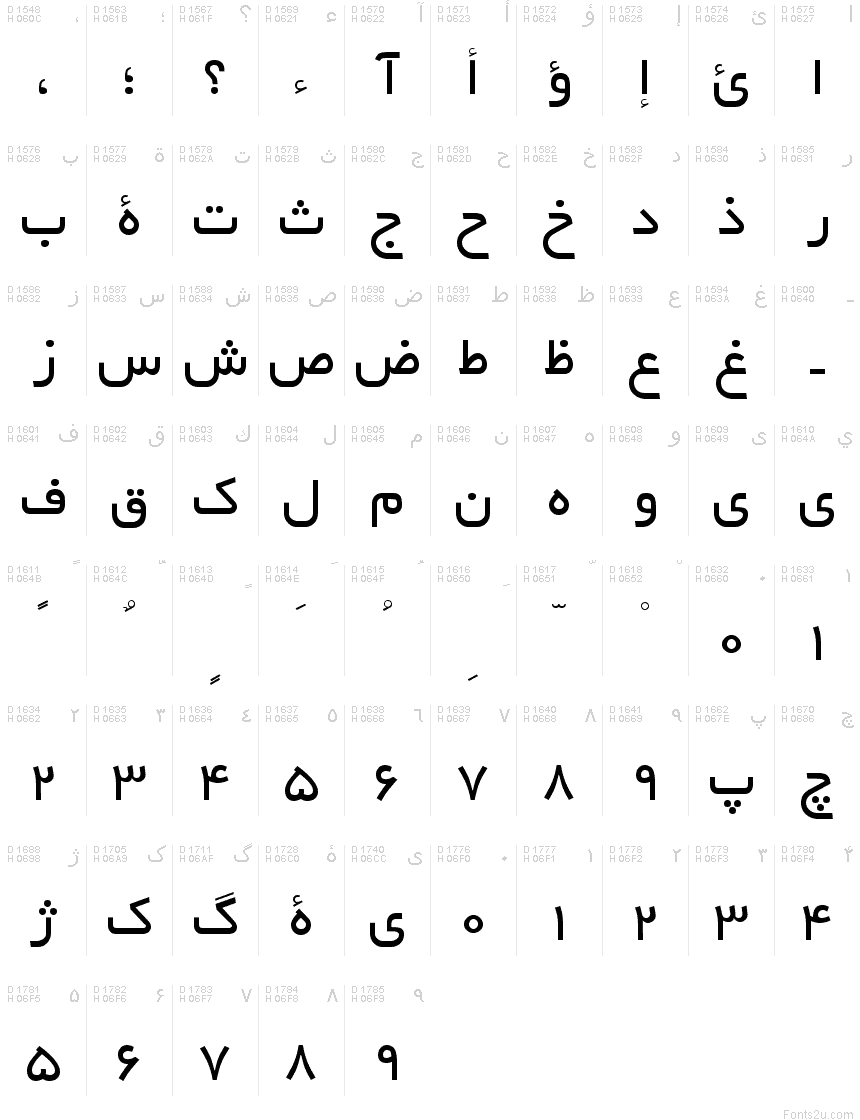
B Yekan, autorstwa Borna Rayaneh, to darmowy, nowoczesny arabski krój bezszeryfowy o spokojnym, współczesnym charakterze. Litery wyglądają na kompaktowe i płynne, z zaokrąglonym ruchem i równomierną grubością, co nadaje pismu praktyczny, miejski klimat, zamiast kaligraficznego wyrazu.
Sprawia to, że krój ten naturalnie sprawdza się w etykietach interfejsów, opakowaniach, śródtytułach redakcyjnych, plakatach i systemach informacji wizualnej, gdzie arabski tekst ma sprawiać wrażenie aktualnego i bezpośredniego. Jako darmowy font, dobrze sprawdza się również w nagłówkach i krótkich projektach brandingowych, ponieważ powściągliwe krzywe utrzymują pismo w czystej i uporządkowanej formie przy większych rozmiarach.